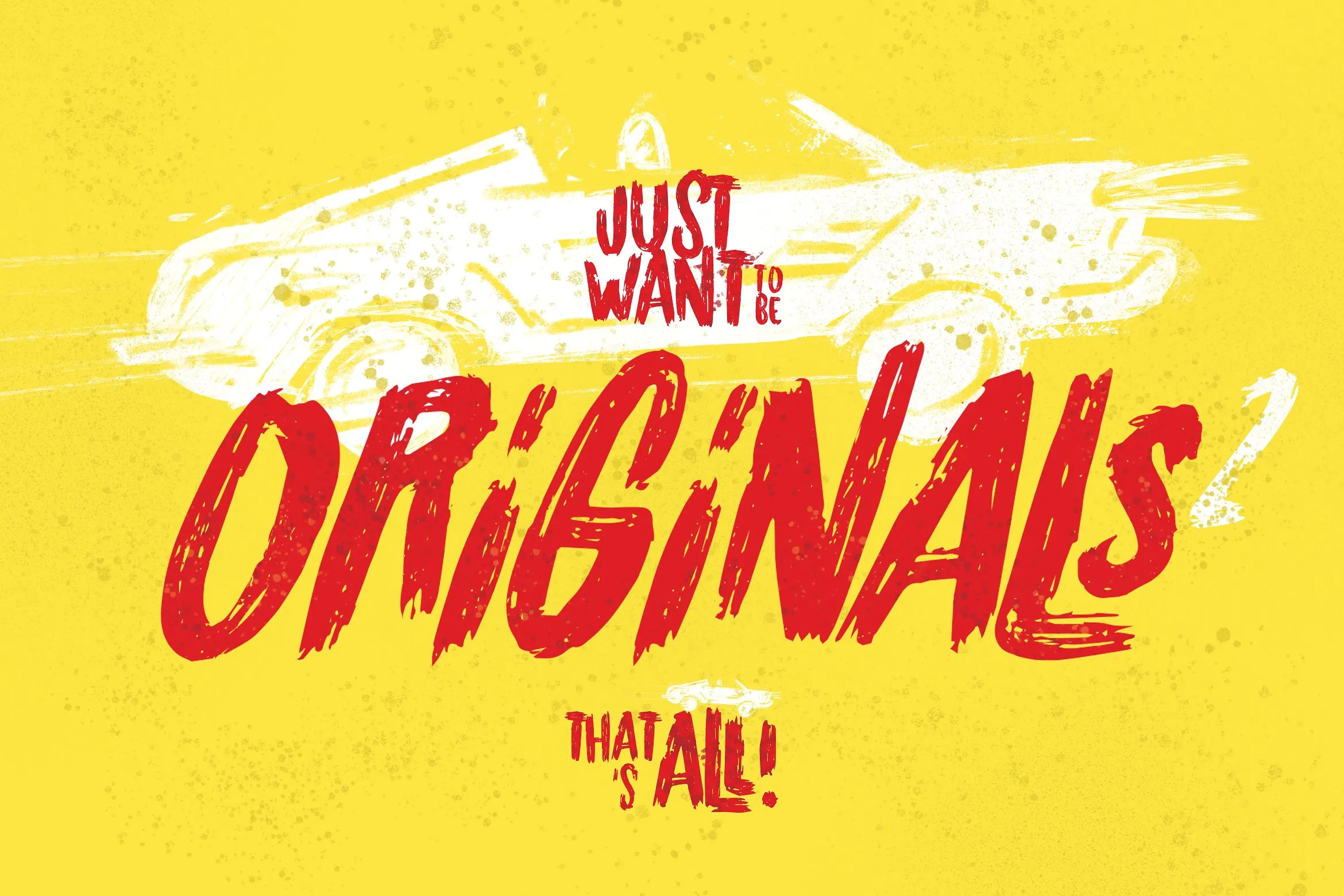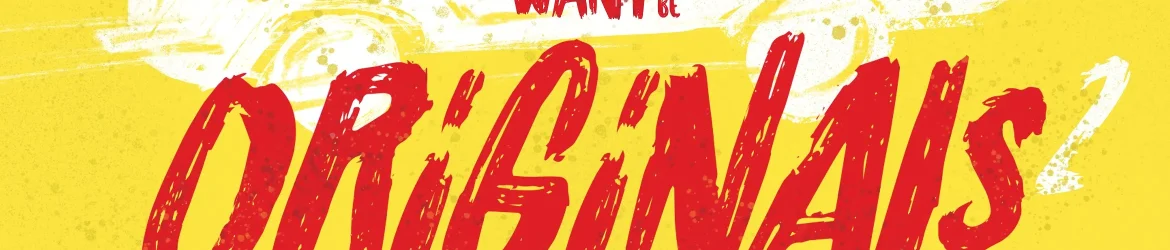
Originals 2 Typeface – Download Grátis
Originals 2 é uma nova adição à família Originals Typeface criada pelo Designer LeoSupply.co. Este tipo de escrita é uma seleção única e divertida de traços, desenvolvida para trazer um toque fresco às suas criações digitais. Com seus detalhes cuidadosamente desenhados a mão, Originals 2 oferece um estilo ideal para uso em estilos criativos como cartazes, camisetas ou cartões. Este fonte é perfeito tanto para projetos de design com temas veranos frescos quanto para aqueles que buscam um ar mais descontraído e descomplicado. Com todas as gílias dos EUA incluídas e disponível nas versões regular, inclinada e borrada, Originals 2 traz um conjunto completo de opções para personalizar seus projetos. Este tipo de fonte é uma escolha inteligente se você está buscando algo que seja igualmente útil e atraente para qualquer projeto. Originals 2 não apenas adiciona valor à sua lista de tipos de fontes, mas também permite que você ofereça um toque único e personalizado a seus projetos.